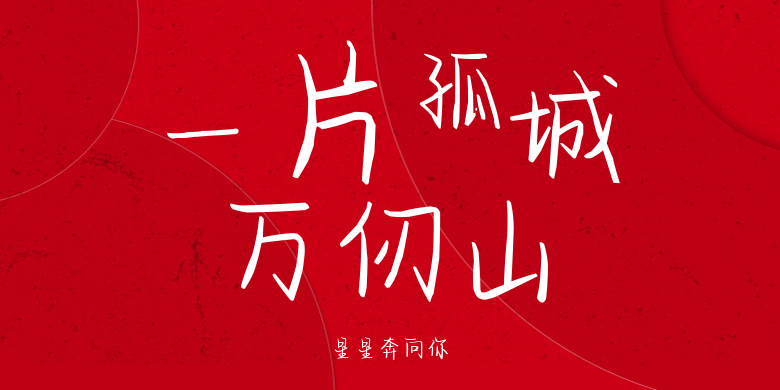
星星奔向你
星星奔向你,这款字体结构工整、笔画清晰,兼顾美观与易读性,适用于标题、正文、海报、包装、LOGO 等多种场景。字形优雅稳定,风格百搭耐看,适配日常排版与创意设计,让文字呈现更舒适、更具质感。星星奔向你一笔一画,皆是细节,以均衡的比例、流畅的线条打造舒适视觉体验,字形端正大气,风格简约现代。无论是商业设计、品牌宣传还是日常排版,都能轻松驾驭,让文字更有格调与力量。星星奔向你字体下载。